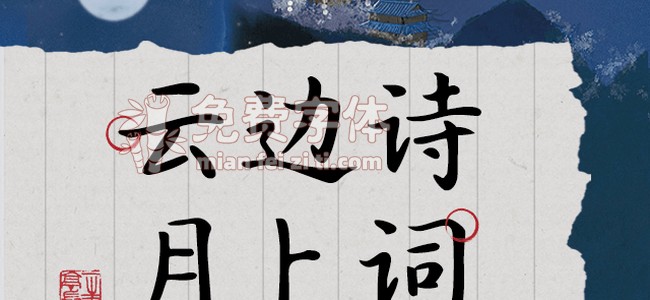
Aa云边诗 月上词
字体名称: Aa云边诗 月上词
Aa云边诗 月上词是一款不错的艺术字体,由Aa字库出品,字体笔触适中,字形端正,具有很好的视觉感,适合应用于艺术设计、平面宣传设计、网页设计,书法字帖等领域,需要的朋友可以前来本站下载。
本款“Aa云边诗 月上词”是一款书写很新颖的字体,字体大方,适合各种设计作品使用!欢迎下载!